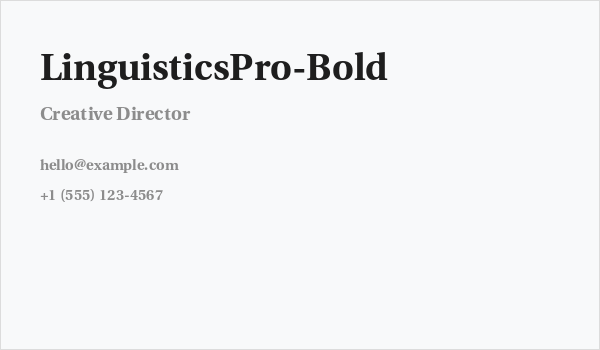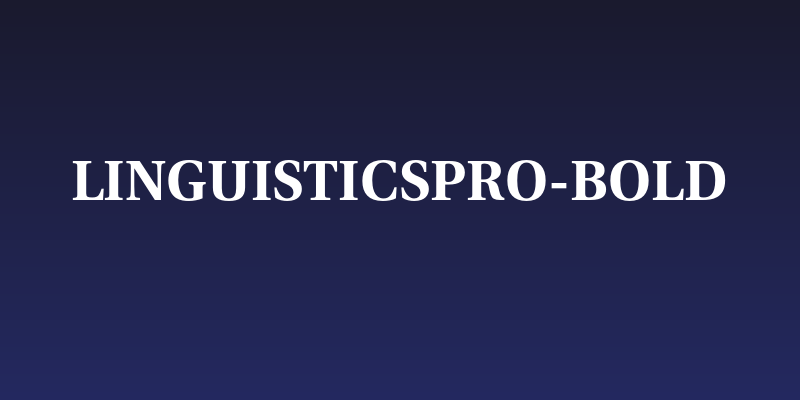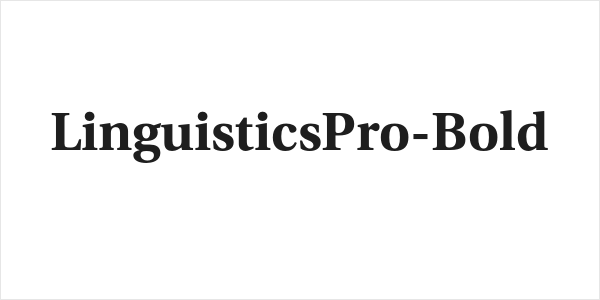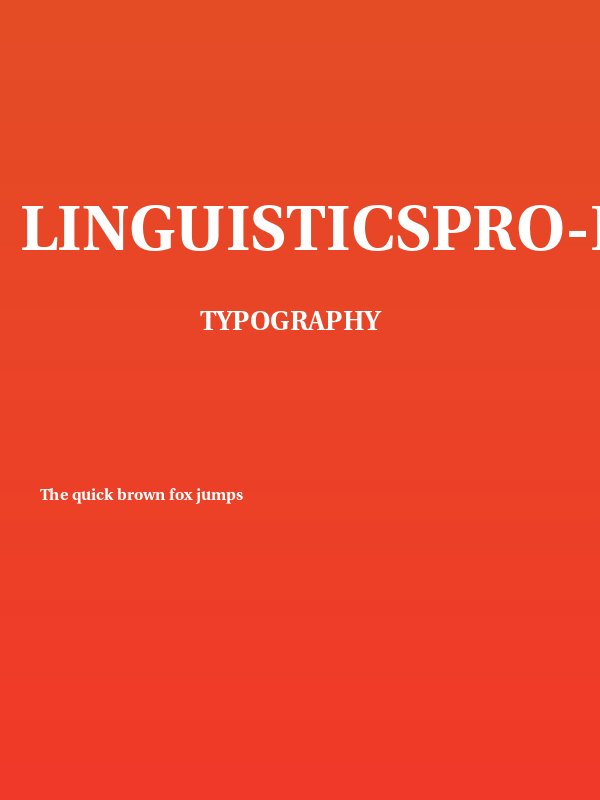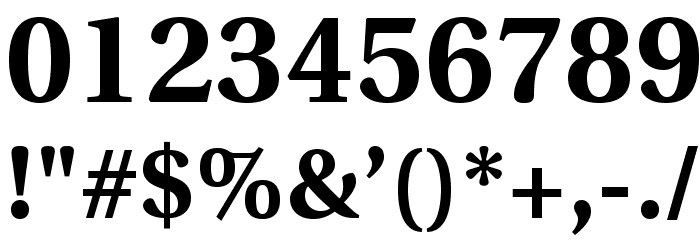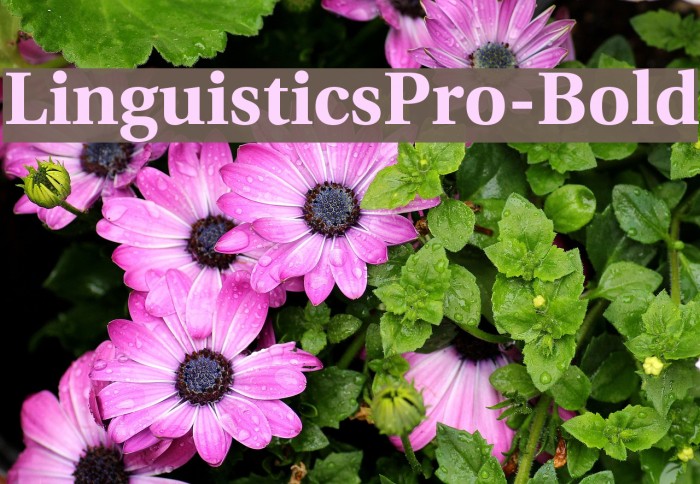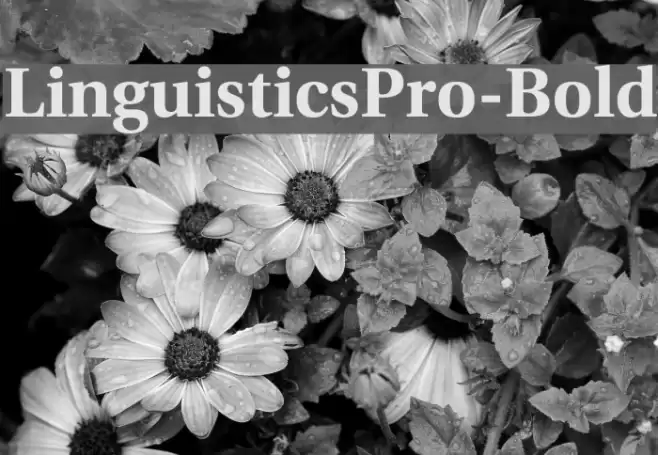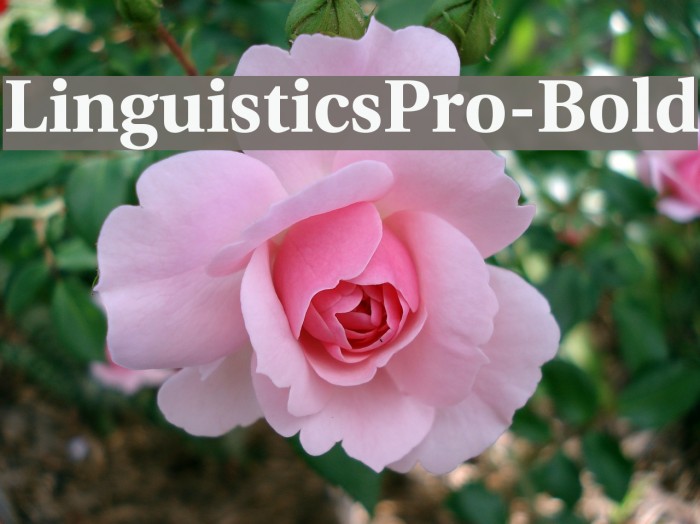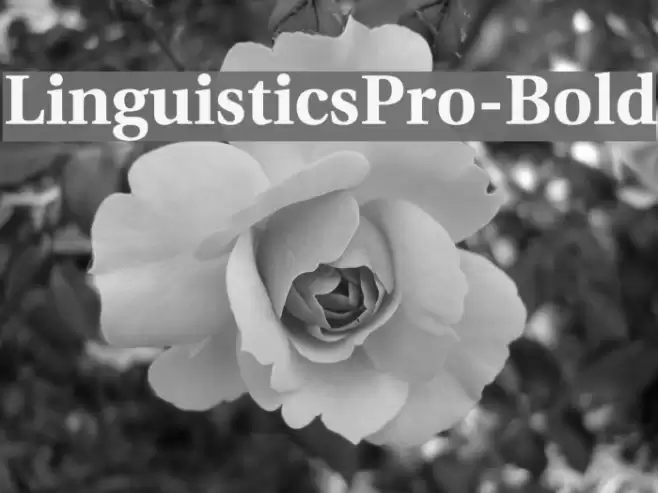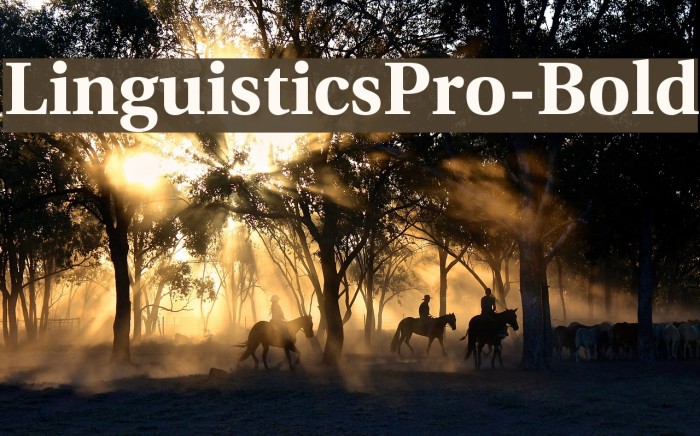
LinguisticsPro-Bold Font
| Projetos propostos | Ideal for book covers, formal invitations, academic publications, and branding materials that require a traditional and authoritative look. |